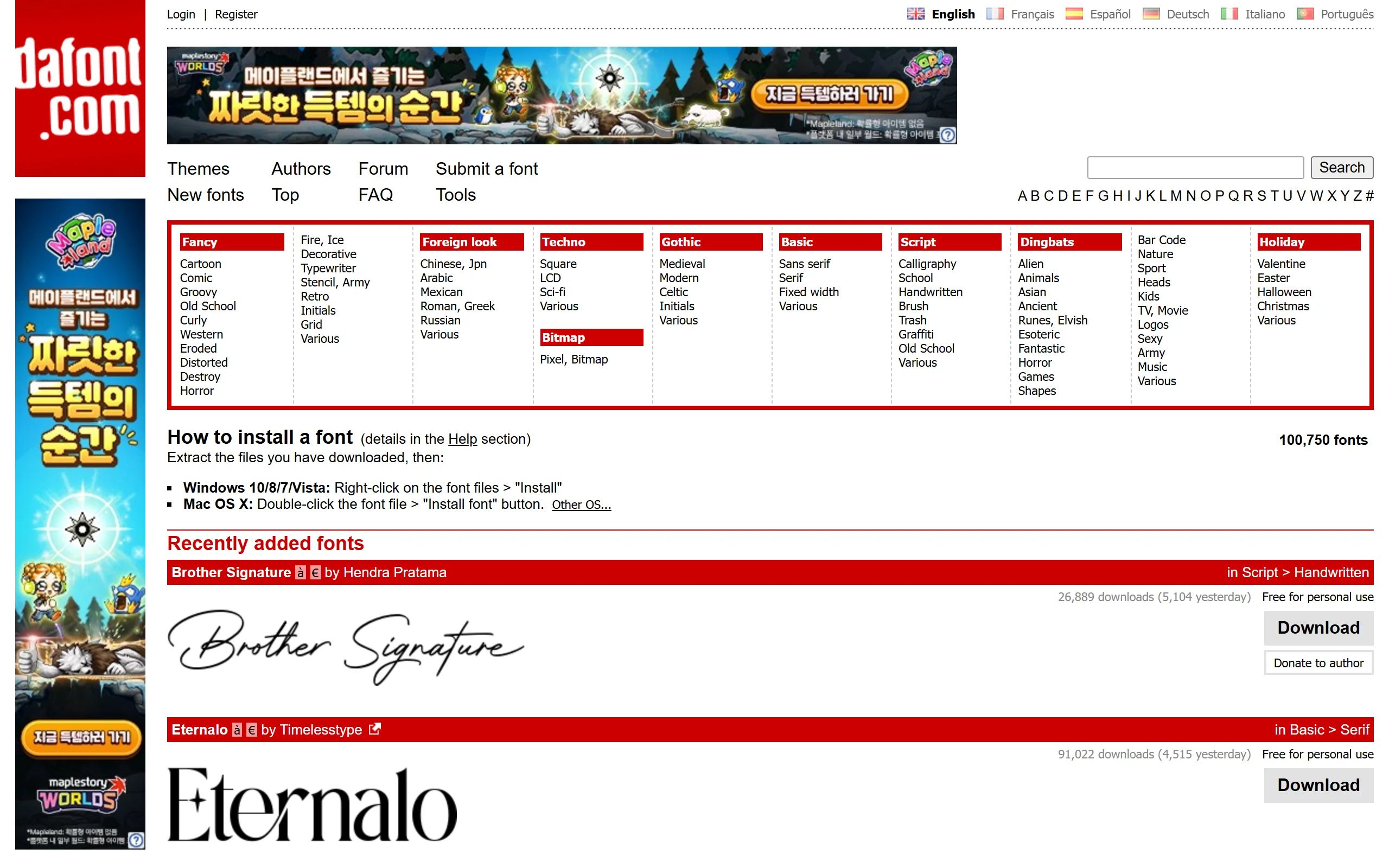
Descripción General
DaFont es un sitio web increíblemente grande y popular para descargar fuentes gratuitas. Es reconocido por su vasta y diversa colección de tipografías, a menudo creadas por diseñadores independientes y aficionados, destinadas principalmente a uso personal y no comercial. Enorme biblioteca de fuentes gratuitas: Esta es la principal atracción de DaFont. Aloja decenas de miles de fuentes, cubriendo virtualmente todas las categorías imaginables, desde estilos manuscritos y cartoon hasta tipografías decorativas y retro. Casi siempre puedes encontrar algo único y creativo aquí. Navegación y descarga simples e intuitivas: La interfaz del sitio web es muy fácil de usar. Puedes navegar por las fuentes por varias categorías, temas, diseñadores o orden alfabético. Cada página de fuente ofrece vistas previas detalladas y permite escribir texto personalizado para pruebas, y el proceso de descarga es extremadamente sencillo. Soporte para proyectos personales y entusiastas: DaFont proporciona una plataforma para muchos diseñadores tipográficos independientes y creadores aficionados para mostrar y compartir su trabajo. Una gran cantidad de fuentes son 'Gratis para uso personal', lo que las hace ideales para estudiantes, aficionados y proyectos personales. Limitaciones y consideraciones importantes La licencia comercial requiere precaución: Este es el punto más crucial al usar fuentes de DaFont. La mayoría de las fuentes son gratuitas solo para uso personal. Si planeas usar una fuente para cualquier proyecto comercial (incluyendo vender productos, crear logotipos de marca, sitios web o anuncios), debes revisar cuidadosamente la información de licencia de cada fuente y típicamente necesitas contactar al diseñador para comprar una licencia comercial. El sitio web indica claramente los diferentes tipos de licencia. Calidad variable: Debido a la amplia gama de fuentes y la naturaleza independiente de muchos creadores, la calidad del diseño, la completitud del conjunto de caracteres y el refinamiento técnico de las fuentes pueden variar. Los usuarios necesitan ejercer su propio juicio al seleccionar fuentes. DaFont es una vasta fuente de inspiración creativa y un tesoro de fuentes gratuitas, especialmente adecuado para proyectos personales, prototipado y exploración de estilos novedosos. Sin embargo, al usar fuentes de DaFont, los usuarios deben revisar meticulosamente y entender los términos de licencia de cada fuente para evitar cualquier riesgo de derechos de autor comerciales. Para aquellos con presupuestos limitados que necesitan una gran cantidad de fuentes únicas y no comerciales, o para disfrute personal y aprendizaje, DaFont es un recurso indispensable.
DaFont es un vast source de creativo inspiración y treasure trove de gratuito fuentes, especially suitable para personal projects, prototipado, y exploring novel styles. However, cuándo usando fuentes de DaFont, usuarios debe meticulously check y understand licencia terms para cada fuente avoid cualquier comercial derechos de autor risks. para esos con limitado budgets quién necesidad grande quantity de único, non-comercial fuentes, o para personal enjoyment y learning, DaFont es un indispensable recurso.
Características Principales
- 1. Massive gratuito fuente biblioteca: este is DaFont's core attraction. ello hosts tens de miles de fuentes, covering virtually cada category imaginable, de handwritten y cartoon styles decorative y retro typefaces. tú puede almost siempre encontrar something único y creativo here.
- 2. simple & intuitivo Browsing y Downloading: sitio web's interface is muy amigable. tú puede navegar fuentes por varios categories, themes, diseñadores, o alphabetical order. cada fuente page ofrece detailed previews y permite tú type custom text para testing, y descargar proceso is extremely straightforward.
- 3. soporte para Personal Projects & Enthusiasts: DaFont proporciona plataforma para muchos independent type diseñadores y amateur creadores escaparate y compartir su trabajo. grande número de fuentes son "gratuito para personal usar," haciendo ellos ideal para students, hobbyists, y personal projects.
- Limitations & importante Considerations
- Varying Quality: Due amplia gama de sources y independent nature de muchos creadores, diseñRA quality, character conjunto completeness, y technical refinement de fuentes puede vary. usuarios necesidad exercise su own judgment cuándo selecting fuentes.